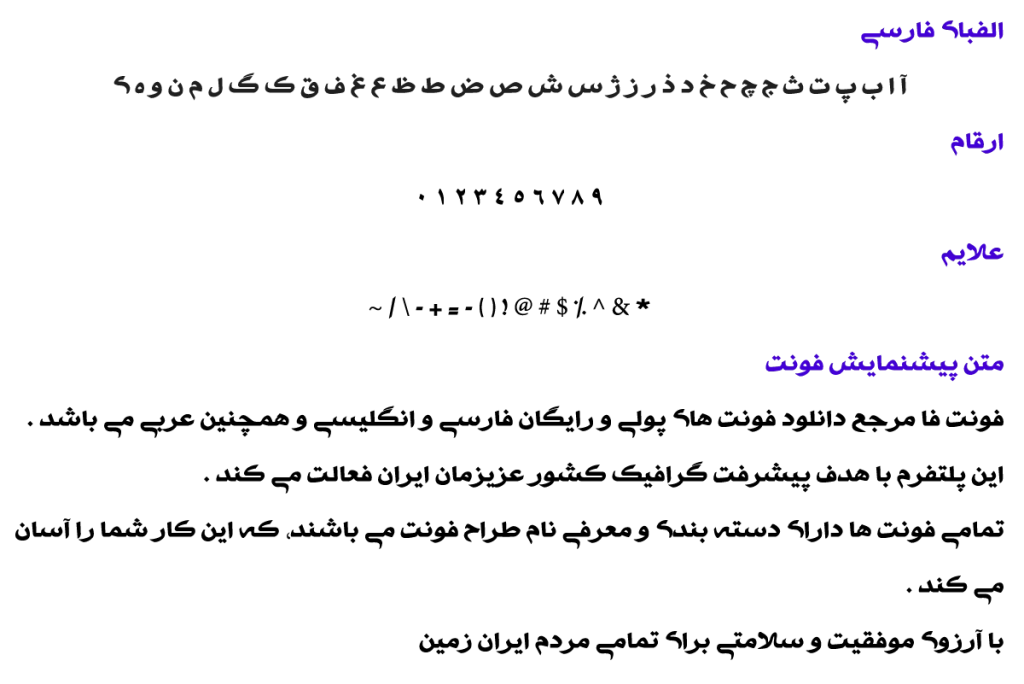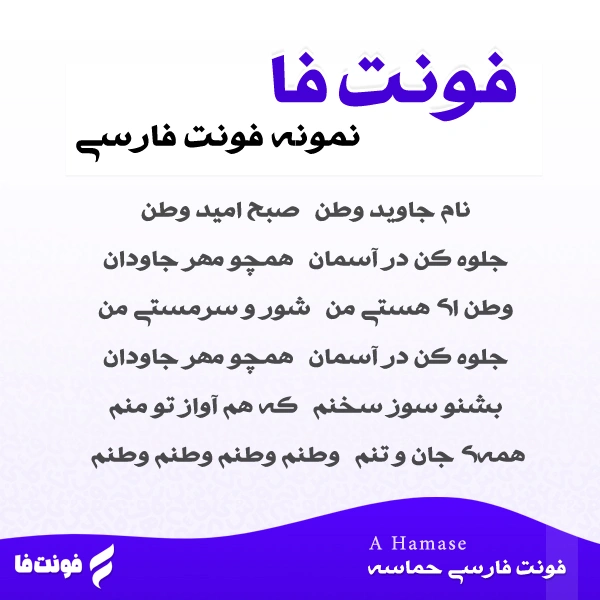
فونت فارسی حماسه – A Hamase
سال ساخت فونت: 1392
طراح فونت: علی سواری نوع فونت: فونت عنوان
پیشنمایش فونت حماسه
توضیحات و معرفی فونت حماسه
فونت فارسی حماسه ( A Hamase ) از مجموعه فونت های آزاد می باشد، و نیز نوع فونت عنوان می باشد.
فونت خوشگل مربوط توسط علی سواری در سال 1392 طراحی و ساخته شده است.
این تایپ فیس براساس فونت تهران و با اضافه کردن چندین ویکتور انقلابی و تغییرات کوچک بازطراحی شده است.
و نیز فونت A Hamase در یک وزن پر رنگ است.
- A Hamase Bold
پیش نمایش این تایپ فیس را که شعر زیبای «وطن» با آن نوشته شده، در تصویر زیر مشاهده میکنید.